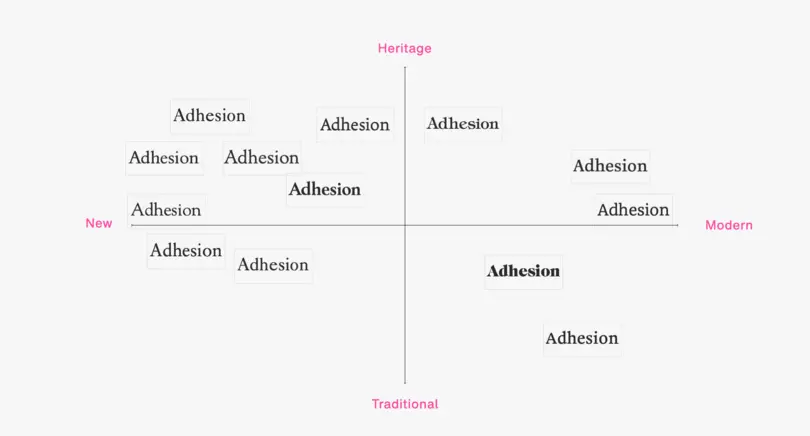
Noch nicht die richtige Schrift gefunden? Hier ein paar Tipps
​​​Ihnen ist sicherlich wichtig, dass die visuelle Identität Ihrer Marke auf einer soliden Grundlage steht, denn ein konsistentes Branding kann den Umsatz um 33 Prozent steigern. ​​
Es ist wieder so weit: Sie sitzen am Schreibtisch, um ein neues Designprojekt zu beginnen. Eine der ersten Aufgaben ist die Wahl einer Schrift. Sie beginnen mit einer Internet-Suche und kämpfen sich durch endlose Listen mit Fonts. Das Angebot erschlägt Sie geradezu.
Nach stundenlanger Recherche finden Sie schließlich eine Schriftenfamilie, die Ihnen zusagt. Allerdings haben Sie das Gefühl, dass sie in kleiner Größe auf dem Smartphone kein gutes Bild abgibt. Sie entscheiden sich daher für den zweiten Favoriten, fragen sich aber, ob der Stil zur Zielgruppe beziehungsweise zur Branche passt.
Ehe Sie sich versehen, ist aus der kleinen Recherche ein halber Tag geworden, den Sie mit dem Durchstöbern von Schriften verbracht haben. Am Ende haben Sie die Liste auf ein Dutzend heißer Kandidaten eingegrenzt, aber Sie werden das Gefühl nicht los, dass die perfekte Lösung nicht dabei ist. Sie möchten wirklich die beste Schrift für Ihre Marke finden. Wie geht es jetzt weiter?
Es gehört sicherlich zu den schwierigsten Entscheidungen im Design, zum Start eines neuen Projekts aus einer riesigen Auswahl von Schriften die richtige zu finden. Die Suche nach der perfekten Markenschrift ist eine echte Herausforderung. Ganz gleich, ob Sie an einer neuen Kampagne, einer Produkteinführung oder einem Rebranding arbeiten – die Wahl der Schrift ist fundamental: Sie kann die positive Reaktion der Verbraucher um 13 Prozent steigern.
Schrift kann Vertrauen aufbauen und einen langanhaltenden Effekt auf die Verbraucher haben. Natürlich ist die Schrift nur einer von vier visuellen Markenbausteinen neben Farbe, Form und Bildsprache. Aber sie ist der wichtigste, weil unentbehrlich und dauerhaft. Sie ist die Basis für die visuelle Identität einer Marke. Und: Schrift ist umsatzrelevant, denn ein konsistentes Branding kann den Umsatz einer Marke um 33 Prozent steigern.
Zu einem konsistenten Branding gehört eine Schrift, die plattformübergreifend funktioniert. Also werden Sie sich nach einer vielseitig einsetzbaren Lösung umschauen. Die Frage ist aber: Welche Kriterien kennzeichnen eine vielseitige Markenschrift? Entscheidungen im Design sind zum großen Teil subjektiv, so auch die Suche nach der „perfekten“ Schrift. Nach unserer Erfahrung geht es bei der Wahl einer Hausschrift zu 50 Prozent darum, wie sie aussieht, und zu 50 Prozent darum, dass sie das notwendige technische Rüstzeug mitbringt. Wie kann man vor diesem Hintergrund sicher sein, die richtige Wahl für ein Projekt zu treffen?
Die große Zahl der Auswahlkriterien überfordert selbst erfahrene visuelle Gestalter. Wenn Sie nicht weiterkommen oder Schwierigkeiten haben, überhaupt anzufangen, dann treten Sie einen Schritt zurück und stellen Sie sich die folgenden, sehr grundlegenden Fragen:
• Welche Ziele möchten Sie mit der Wahl einer neuen Schrift erreichen?
• Wer ist die Hauptzielgruppe, die Sie ansprechen möchten?
• Welche Art von Markenidentität möchten Sie schaffen?
• Was könnte die Zukunft für Ihre Marke bringen?
An x Y axis is shown and the word "adhesion" in different typefaces is plotted in according to how they match the words heritage, new, modern, and traditional
Die Beantwortung dieser Schlüsselfragen hilft Ihnen dabei, darüber nachzudenken, wie und ob Ihre Designentscheidungen dem Projektziel dienen. Denken Sie dabei auch an die Funktionalität. Sie sollten die Zugänglichkeit, die Lesbarkeit und die emotionale Bindung der von Ihnen gewählten Schrift auf die Probe stellen. Immerhin wird die am besten lesbare Schrift um 33,1 Prozent schneller gelesen als die am schlechtesten lesbare. Wenn Sie nur wenig Zeit haben, um einen guten ersten Eindruck zu hinterlassen, ist die Lesbarkeit ein entscheidendes Kriterium.
Markendifferenzierung und Wahrnehmung in Einklang bringen
Ein hilfreiches Modell für die Wahl der richtigen Schrift im Branding ist ein Koordinatensystem mit den beiden essenziellen Markenwerten als Extrempunkten sowie deren Gegenteil am anderen Ende der Achsen. Positionieren Sie nun Ihre Marke in einem der vier Quadranten. Platzieren Sie daraufhin die von Ihnen ausgewählten Lieblingsschriften in das Koordinatensystem, indem Sie die emotionale sowie die formale Eigenschaft der jeweiligen Schrift als Kriterium zu Rate ziehen. Auf diese Weise reduzieren Sie Ihre Favoritenliste auf jene Schriften, die im selben Quadranten liegen wie Ihre Marke.
Die Verwendung von Frameworks ist ein hilfreiches Werkzeug, um der Wahrnehmung Ihrer Marke auf die Spur zu kommen und gleichzeitig die Stakeholder-Gruppe, für die Sie entwerfen, zu verstehen. Zudem wird auf diese Weise sichergestellt, dass die zukünftige Schrift die Persönlichkeit, die Ambitionen und die Bedürfnisse der Marke genau widerspiegelt. Sie können diesen Rahmen auch nutzen, um mit Schriftkombinationen zu experimentieren. Vielleicht stellen Sie fest, dass Sie zwei Schriften benötigen: eine, die für bestimmte Aufgaben groß gesetzt funktionieren muss und eine ganz andere, die in der mobilen App klein gesetzte Texte gut lesbar wiedergeben soll. Es ist wichtig, dass die von Ihnen gewählten Fonts gut zusammenpassen und mit den Kernwerten der Marke übereinstimmen.
Verwenden Sie eine cloudbasierte Schriftbibliothek
Wenn Sie das nächste Mal vor der Entscheidung für eine Schrift stehen, probieren Sie eine der oben genannten Strategien aus – je nachdem, was für Sie am besten funktioniert. Wie bei allen Aspekten des Designs ist auch die Wahl der Schrift eine Entwicklung. Wenn Marken ihre Identität weiter schärfen, werden sich auch die Bedürfnisse und Kernwerte ändern. Es liegt an Ihnen, auf der Grundlage der Ihnen zur Verfügung stehenden Informationen die beste Entscheidung zu treffen. Als Designer sind Sie für eine Marke die Schlüsselfigur, mit deren Hilfe sie das Gleichgewicht zwischen Markenpersönlichkeit und Markenbedürfnis findet.